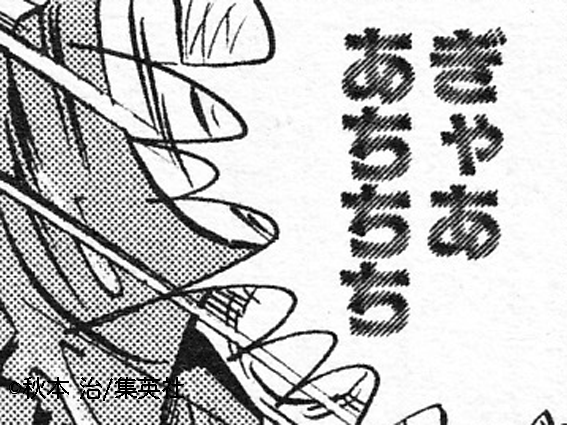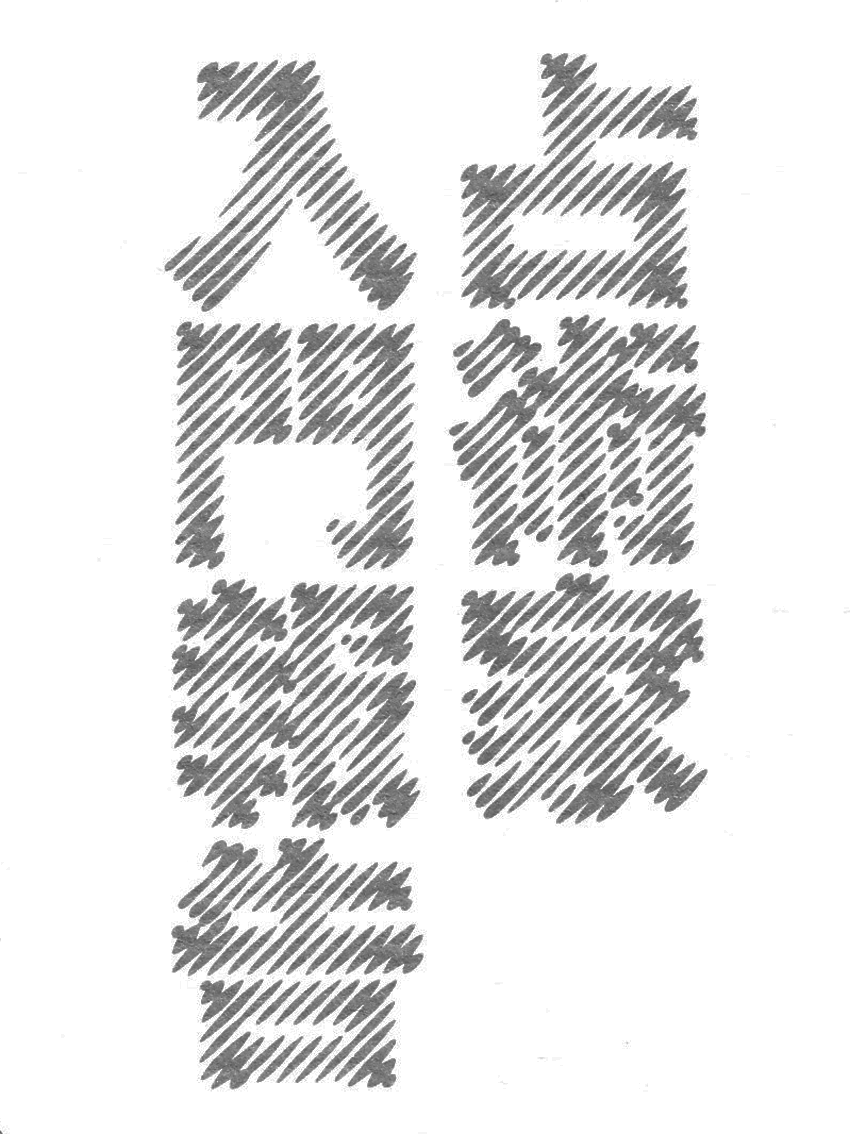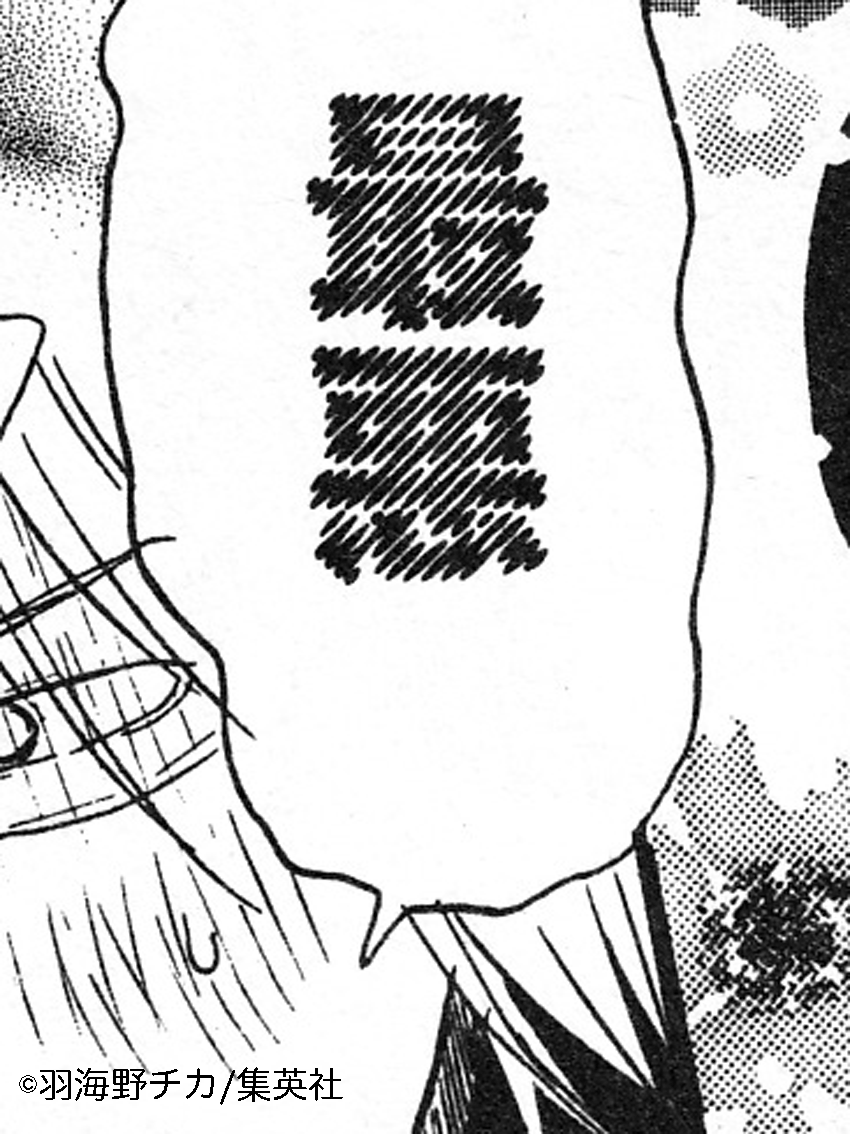
ボカッシイ
粘着質の文字に弱い。
粘着質、というのは、べたっと目の裏にはりつくような字。起伏が大きい字。圧が強く感じられる字。
そういう文字を見ると、つい引き寄せられてしまう。ずっとそう自覚していたのだが、でも実は、その条件にまったく当てはまらない例外がある。〈ボカッシイ〉だ。
〈ボカッシイ〉もやはり現在のDTPでは公開されていないけれど、80年代から90年代にかけてよくつかわれていた写研の写植書体である。前出の〈スーボ〉のように、ユニークで完成度の高いディスプレイ書体がすでに普及していた当時でも、その登場(第七回石井賞)から〈ボカッシイ〉がとにかく異色な存在だったのは間違いない。
なにしろその字形!
およそアウトラインというものがない。
細部がよく見えないくせに、目にするたびに、初めて見るものを見ているような気もする。
前代未聞、という言葉はあまり好きじゃないけれど、三十年経った今もなお「代用書体」さえ出てこない、という事実が、何よりそのことを証明している。
文字を光らせたり陰影をつけたり、ぼかしたりすることは、いまや書体ではなくてもグラフィックソフトをつかえば簡単にできるのかもしれない。しかしテクノロジーを駆使して加工された文字は、よくも悪くもクリアで雑味がなく、合成香料的な印象があるのに対して、〈ボカッシイ〉の方は、私にとって、香りの強いハーブみたいだ。そのなんともいえない微妙なえぐみは、虫がよりつかない成分を自らだしているとしか思えない。
〈ボカッシイ〉の設計者は、後にあの艶書体を制作する今田欣一氏。
伝統的な江戸切子のカットガラスからデザインの着想を得たのだ、ということをどこかで読んだけれど、なるほど、冷たいガラスのように温度の低い文字である。視覚的なインパクトは刺激が強いのに、鎮静作用もあわせもっている、という感じ。
この書体でかかれた言葉には、揮発性のあるメントールみたいに、読後がスース―する清涼感があると思う。
言葉の体温が急激に下がることによって、「興醒め」や「しらける気持ち」、いわゆる現代語で言うところの「引く」という心の距離感が表現されているのはおもしろい。
でもたとえば『こち亀』の両さんが熱湯をかぶってしまった場合。
矛盾するようだが、この場合に書体がふさわしくないかというと、そうは思わない。
その言葉が持つ本来の意味と、書体のイメージの大きな温度差によって、熱湯が沸点に達していることや、脳で温度を感じる前に身体が反応しているということが、実際に皮膚で感じていなくても明快に伝わってくる。肌のうえで気化熱が奪われるように、言葉の表面でも同じ現象が起きているのだ。
勿論、この何気ない小さなシーンについて、担当編集者がどれだけ吟味を重ねたのかはわからない。
しかし当時の連載を見ると、ひとコマごと、セリフごとに全部書体を変えていたりして、わずかなしぐさや声音で人間を演じ分ける落語家さながら書体をつかい倒す慧眼には感服する。そして実に500万人もの人々が、そういうものを毎週読んでいて何も不思議に思わなかった、という事実にも。
こんな書体があるなんて気づかなかった、というひとこそ、実は何度も味わっているかもしれない。
無意識のうちに出会ったもの、目にしていたものが、記憶のなかで複雑な屈折を生み、ひとつとして同じものはない表情をプリズムのようにうつしだす。
ほんとうはそんな文字にいちばん弱いのである。